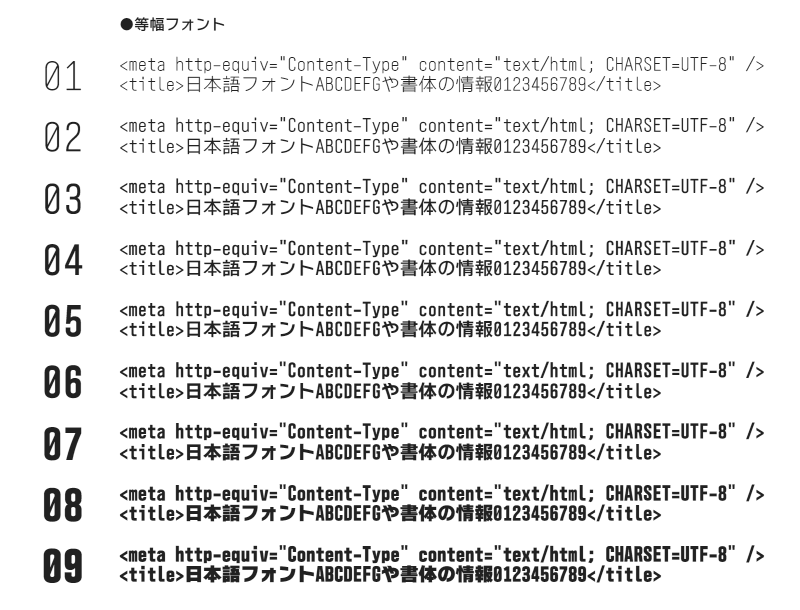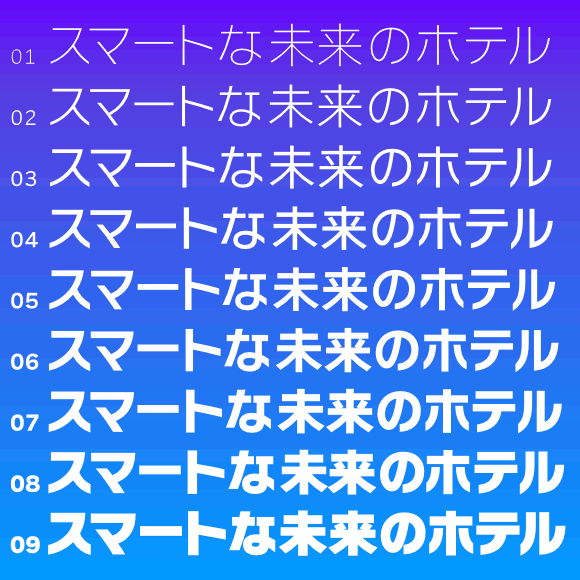
フォント名
デザイン 水平垂直に処理された「かな文字」と、落ちついた雰囲気の「漢字」が、スマートな文字組イメージを創り出し、大きめにデザインされたカタカナが、見やすさや読みやすさを向上させます。
太さが9種類あるので、使用環境や目的に合った最適なフォントが選べます。
等幅バージョンは、英大文字のアイ「I」と英小文字のエル「l」数字のいち「1」や、英大文字のオー「O」と数字のゼロ「0」が、はっきり区別がされているので、URL表記やプログラム編集などにぴったりです。
連想されるイメージ
寄せられたコメントから抜粋
テレビで毎日目にしている・見やすい・そのままロゴに使える・すっきり・洗練されている・変なクセがない・曲線がキレイ・細いのは美しく、太いのは力強い・文字がうまく並ぶ・カッコイイ・オシャレ